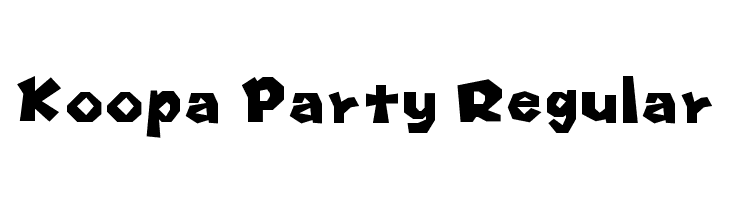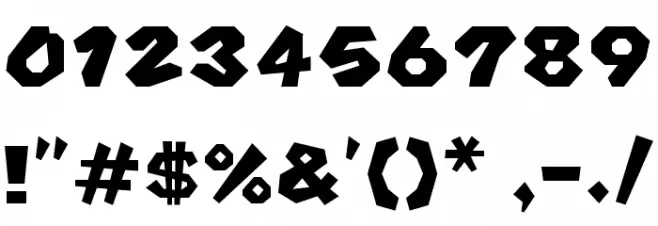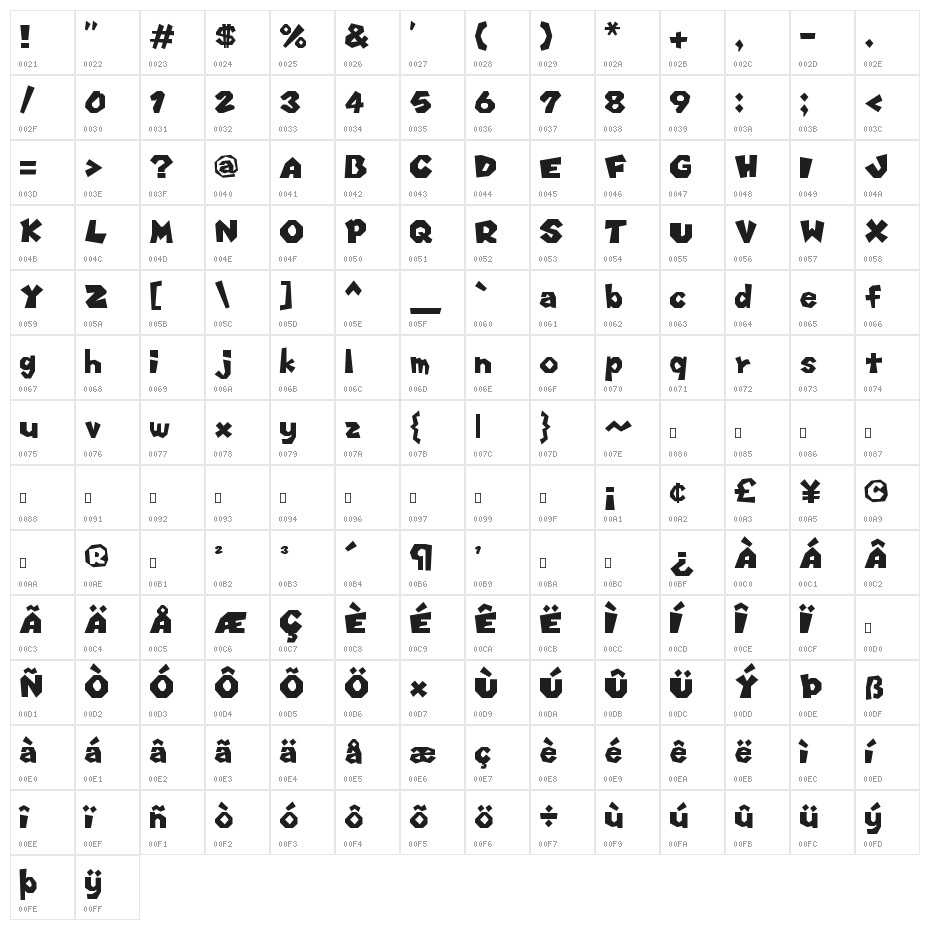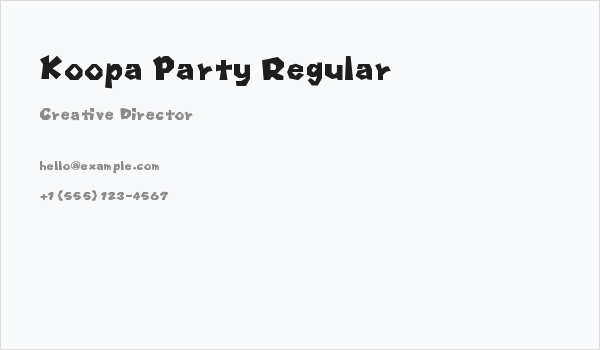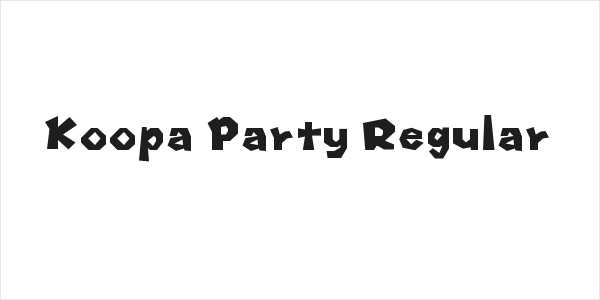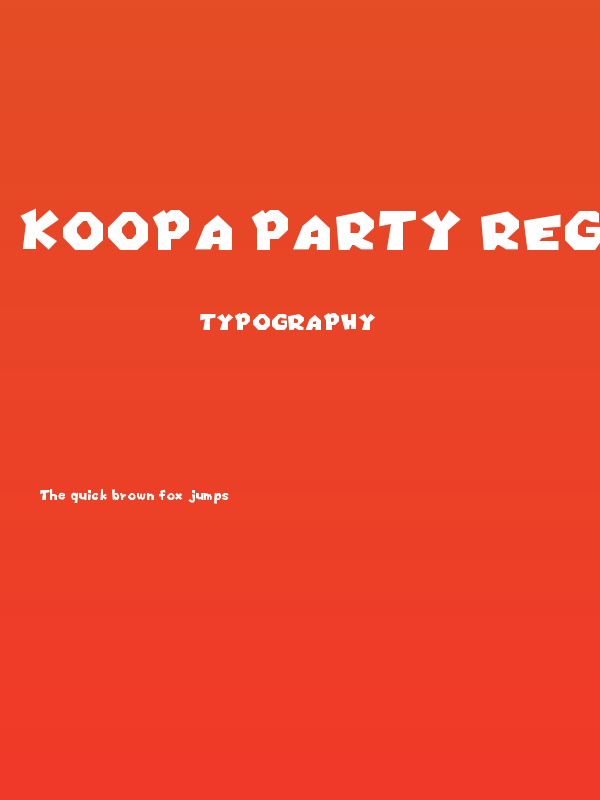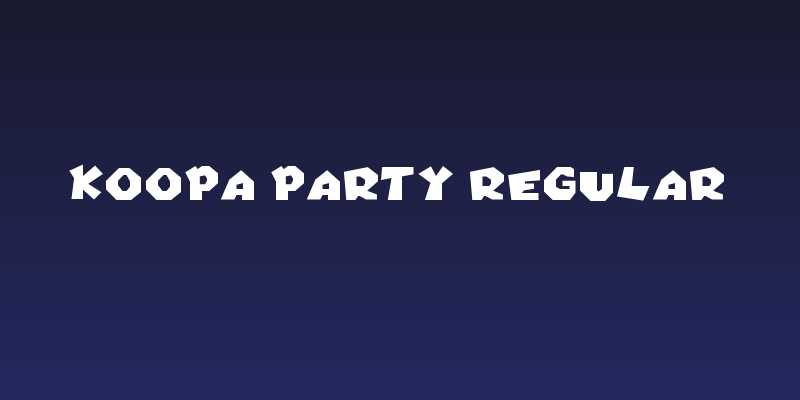
Koopa Party Regular Font
| 全体的なスタイル | Playful, Energetic, Quirky |
| おすすめプロジェクト | Ideal for children's book covers, party invitations, video game graphics, and playful branding. |